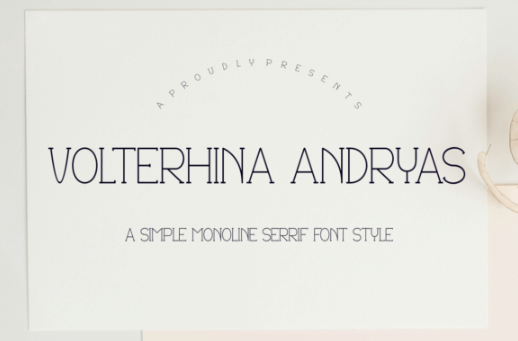
[Creativefabrica] Volterhina Andryas Font (2022)
"Volterhina Andryas" - это ΡˆΡ€ΠΈΡ„Ρ‚ элСмСнта Serif, Π½ΠΎ ΠΎΠ½ Π»ΠΈΠ½ΠΎΠ²Π°Π½Π½Ρ‹ΠΉ, Π»Π΅Π³ΠΊΠΎ читаСтся ΠΈ Ρ…ΠΎΡ€ΠΎΡˆΠΎ смотрится ΠΏΡ€ΠΈ использовании Π² ΠΎΡ‚Π½ΠΎΡˆΠ΅Π½ΠΈΠΈ описания ΠΏΡ€ΠΎΠ΄ΡƒΠΊΡ‚Π°.